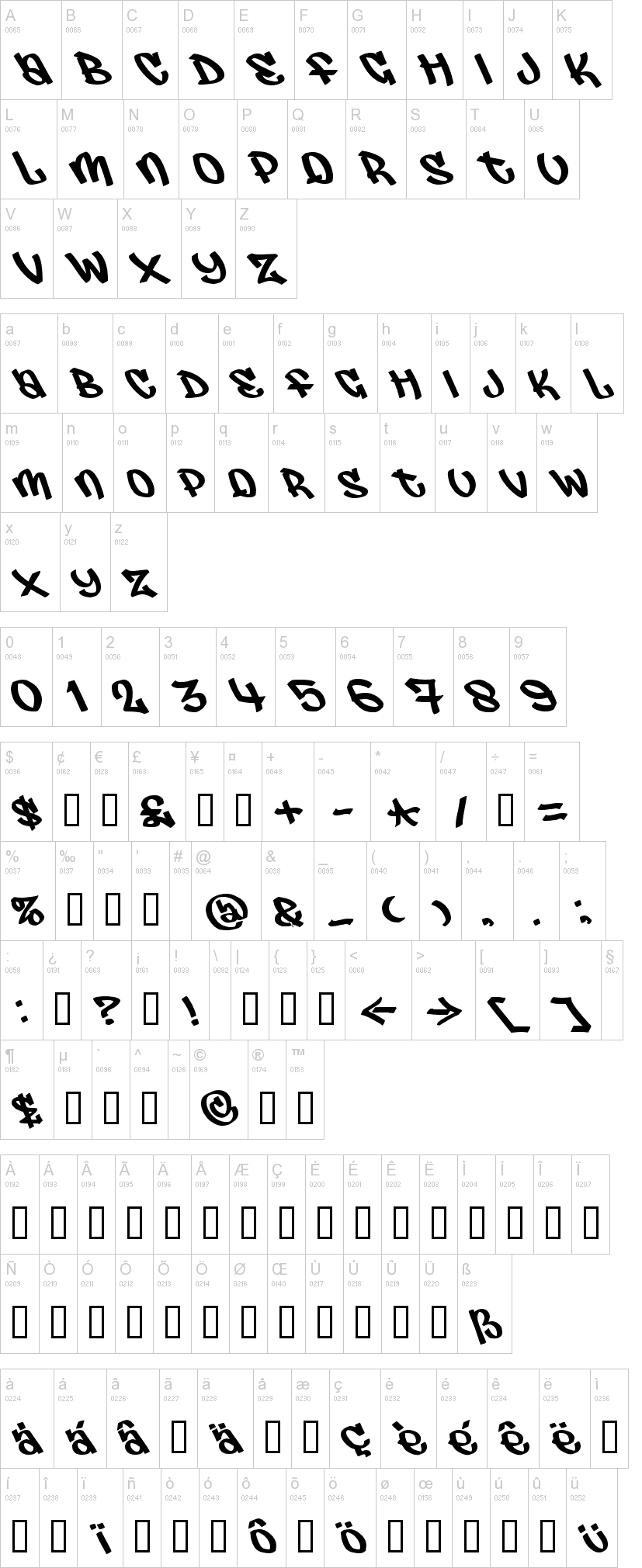
Judas是一款自由字体,它的设计灵感来自于希腊文和英文的手写体。它的风格独特,又同时具有现代感和复古感。 Judas字体的笔画粗细不一,有时会在同一个字母中交替出现,这种设计使得字体看起来很有动感。此外,Judas字体还加入了一些装饰元素,例如字母顶端的小点,以及一些斜线和曲线。 这种字体非常适合设计师在海报、标志、包装、书籍和印刷品等方面使用。由于它的独特性和现代感,Judas字体也被许多品牌和公司用于它们的标识设计中。 总的来说,Judas字体是一种非常具有艺术性和创意性的自由字体,可以为设计师们提供丰富的设计选择。内容介绍
Judas是一款非常不错的手写艺术字体,具有很好的视觉感,适合于文化类的宣传设计、商业类品牌的广告和产品包装设计以及个性化文字排版等较多场景。